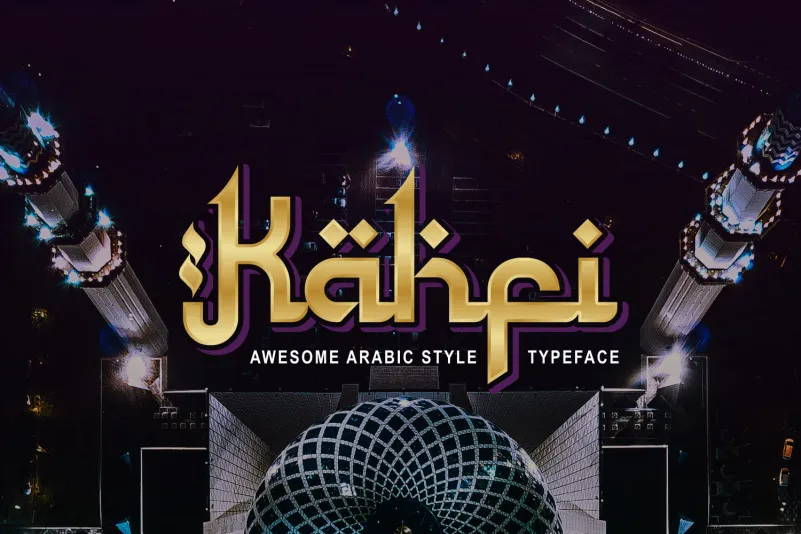
Kahfi Typeface – Download Grátis
Kahfi Typeface é uma tipografia não-latinica que transmite a essência do estilo árabe incorporando letras latinas de forma única. Este tipo de letra é perfeitamente adequado para qualquer projeto gráfico que busque um toque de arredores mediterrânicos e orientais, criando ambientes vibrantes e vibrantes em projetos que exigem uma atmosfera distinta do Oriente Médio. Com sua estrutura elegante e sinergia com letras latinas, Kahfi Typeface oferece flexibilidade para a criação de designs variados, desde gráficos publicitários até embalagens de produtos gourmet que desejam capturar o interesse dos consumidores com um design único e intrigante. Nesse contexto, a fonte é uma ferramenta valiosa para designers profissionais e amadores buscando explorar o vasto universo das tipografias não-latinas.